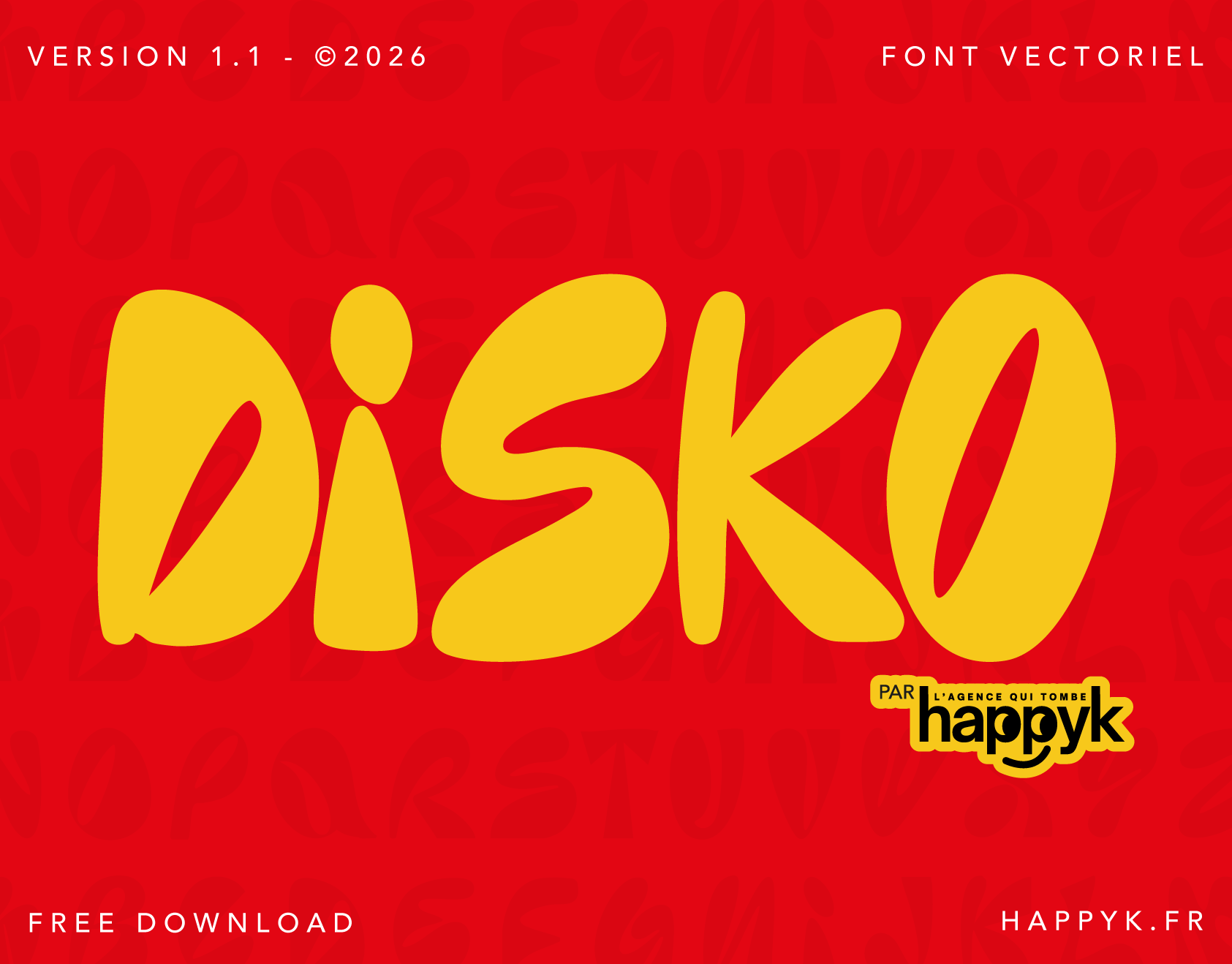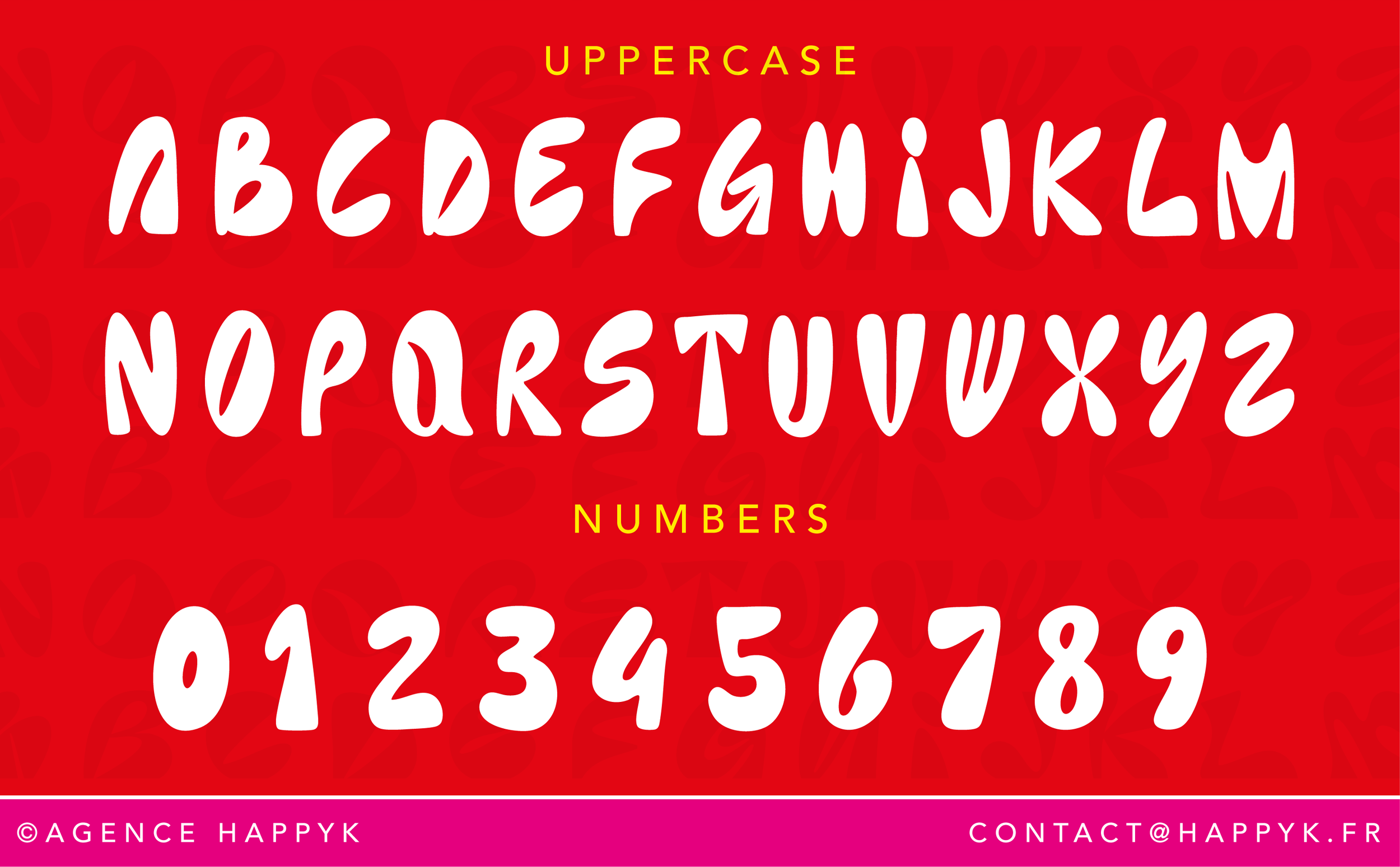
DISKO
La police qui arrive en avance à la soirée.
Inspirée des néons, des boules à facettes et des samedis soirs qui finissent trop tard, DISKO transforme n’importe quel titre en événement.
Parfaite pour les marques qui aiment se faire remarquer. 🕺🪩✨